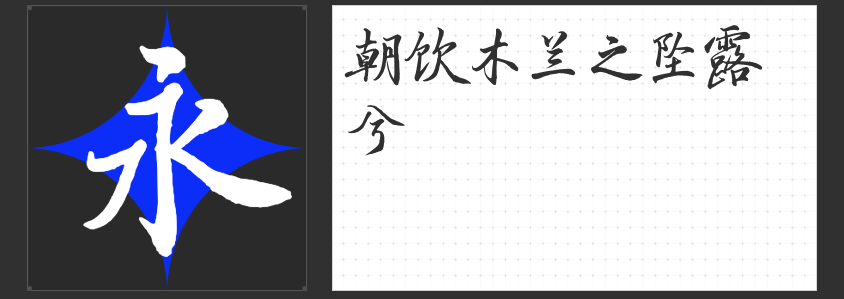
励志类型海报设计通过这四款精选字体展现!
在设计励志意义的海报时,选择适合的字体能够大大提升作品的感染力和视觉效果。今天为大家推荐四款特别适合励志海报设计的字体。
这款字体以其独特的青春活力和动感十足的设计,能够瞬间抓住观众的眼球。它简洁而不失个性,特别适合用于表达年轻人追求梦想、勇敢向前的精神。在励志海报中,这款字体可以很好地传递积极向上的正能量。
这款字体是一款清新的手写体,给人一种热情洋溢的感觉。它的设计既现代又富有力量感,非常适合用于强调目标、梦想和努力的主题。在海报设计中,使用这款字体可以营造出一种积极向上的氛围,激励人们不断前行。
3.云书法玉兰行楷体
这款字体融合了传统书法的韵味和现代设计的元素,呈现出一种优雅而富有韵味的效果。它的笔画流畅自然,字形匀称美观,特别适合用于书写励志名言或标语。在海报设计中,使用这款字体可以提升整体的文化底蕴和艺术感。
这款字体以其细腻的笔触和独特的风格,深受设计师们的喜爱。它的设计灵感来源于钢笔书写,每一个笔画都充满了力量和韵律感。在励志海报中,使用这款字体可以增添一份精致和优雅,让作品更加引人注目。
总之,这四款字体各具特色,都非常适合用于励志海报的设计。选择适合的字体不仅可以提升海报的视觉效果,还能更好地传达出作品的主题和意境。希望这些推荐能够对你的海报设计有所帮助!